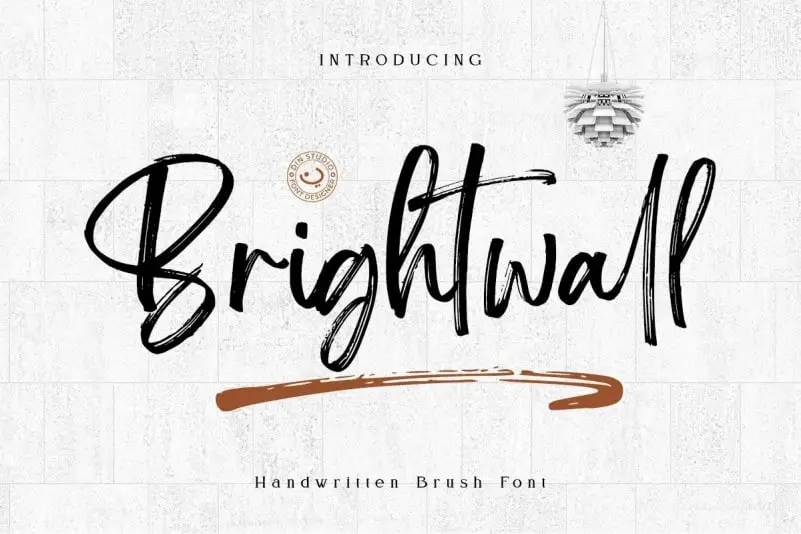
Brightwall Brush Font – Fonte Grátis
Brightwall Brush Font
A Brightwall Brush Font é uma fonte de traço que oferece um toque natural e autêntico para seus projetos de design. Ela foi criada pela Din Studio usando uma ferramenta manual de pincel, resultando numa tipografia perfeitamente natural com tons e texturas únicas. Esta fonte é a escolha ideal para quem procura algo mais elaborado e único, seja para criar uma marca memorável, imprimir mensagens em camisetas ou até mesmo adicionar um toque especial a qualquer projeto de design que precise de um ar sofisticado. Com sua combinação perfeita de beleza natural e força visual, a Brightwall Brush Font é certamente o companheiro perfeito para aqueles buscando expressar suas ideias de maneira única em diferentes tipos de mídia.